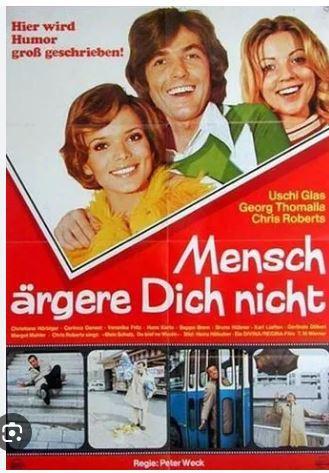
Suche die Schrift, die in der Tipico-Werbung beim Sport-Sender DYN läuft und die Schrift aus einer Apotheken-Zeitung
Kannst Du zur Apotheken-Zeitung ein paar mehr Details liefern?
Diesen Ausschnitt habe ich aus einer Zeitschrift aus meiner Apotheke kopiert. Der Artikel beschrieb das Spiel: "Mensch ärgere Dich nicht". Die Frage ist, welche Schrift ist das?Menschrgere.JPG.509ba3b68131aabf2858a28e0c91b8da.JPG
Leider weiß ich den Titel der Herausgabe nicht mehr aber ich erhalte regelmäßig den Senioren-Ratgeber aus der Apotheke und in der Ausgabe erinnerte man alte Menschen daran, daß es Gesellschaftsspiele gibt.
Habe neu gesucht und die Schrift "Mensch ärgere dich nicht" im Film Logo von 1972 gefunden. Es müßte also ein Bleisatzschrift sein, denn zu dieser Zeit habe ich als Schriftsetzer noch im Bleisatz gearbeitet. Vielleicht hilft es ja jetzt ein wenig weiter, diese oder ähnliche Schriftart zu finden.
Auf dem Plakat sind ja einige Satzschriften zu finden (Cooper, Helvetica?), trotzdem kann der Titel doch handgeschrieben sein. Die e und c sind doch recht unterschiedlich.
Mich erinnert der Gestus ein bisschen an anthroposophische Schriftarten. Aber da habe ich auch spontan keine gefunden, die weitgehend übereinstimmt.
Dass das aus dem Filmtitel stammt, hat Ralf bereits gestern schon geschrieben und dass das mit an Sicherheit grenzender Wahrscheinlichkeit Handarbeit ist, da die gleichen Buchstaben e und h unterschiedliche Formen haben, steht auch schon länger im Raum.